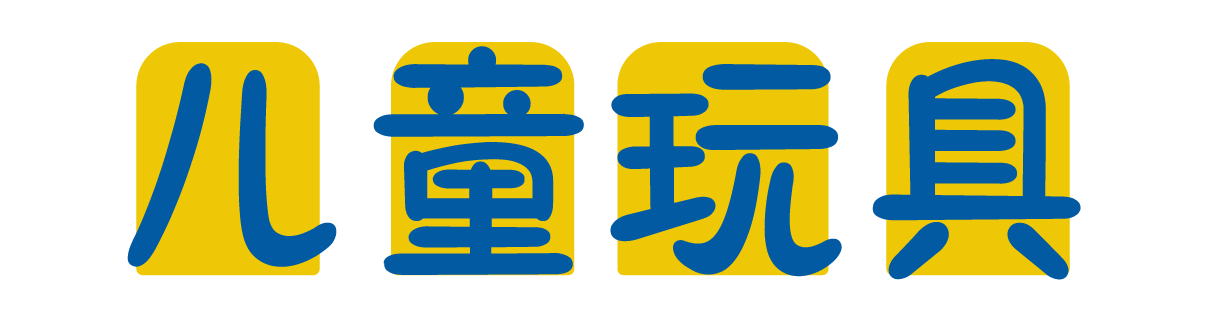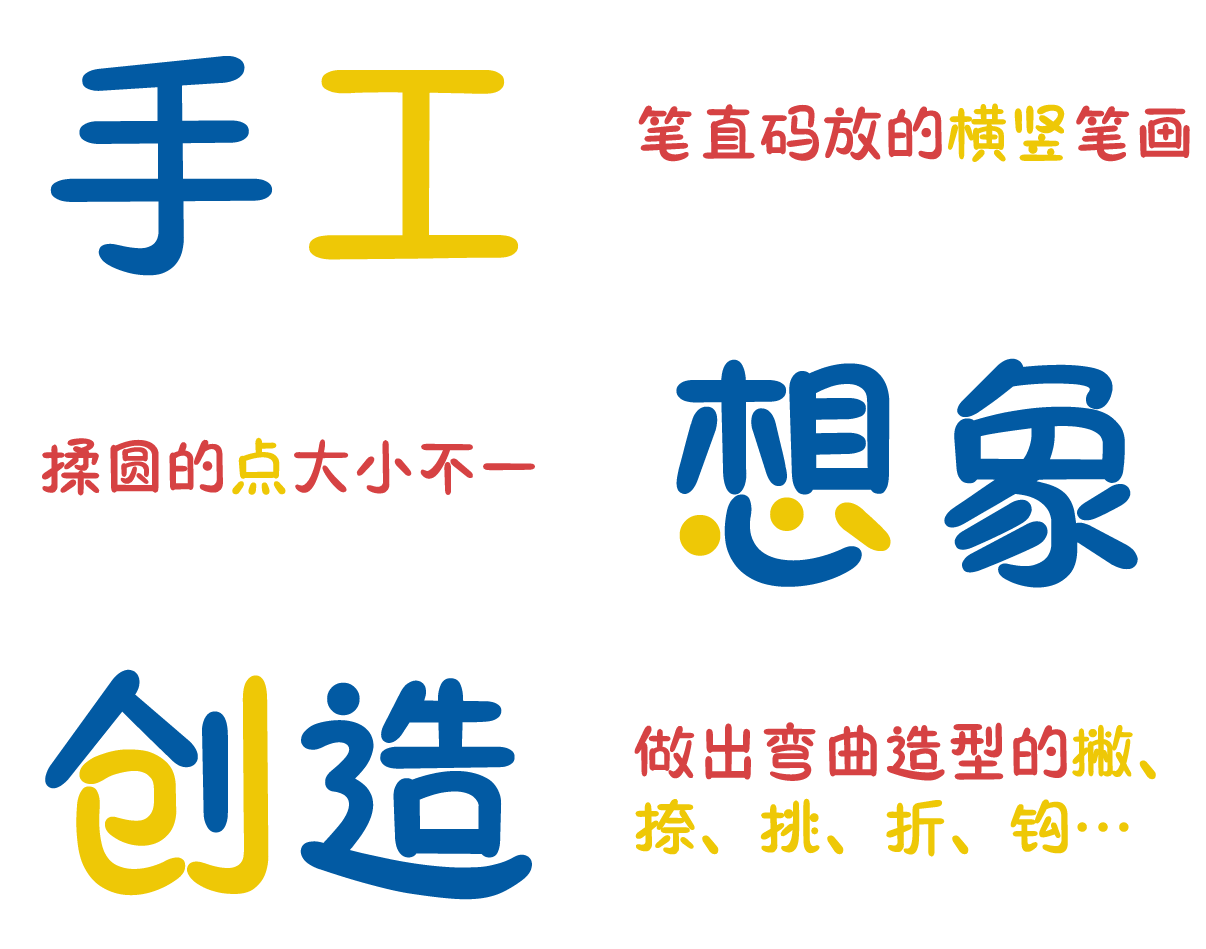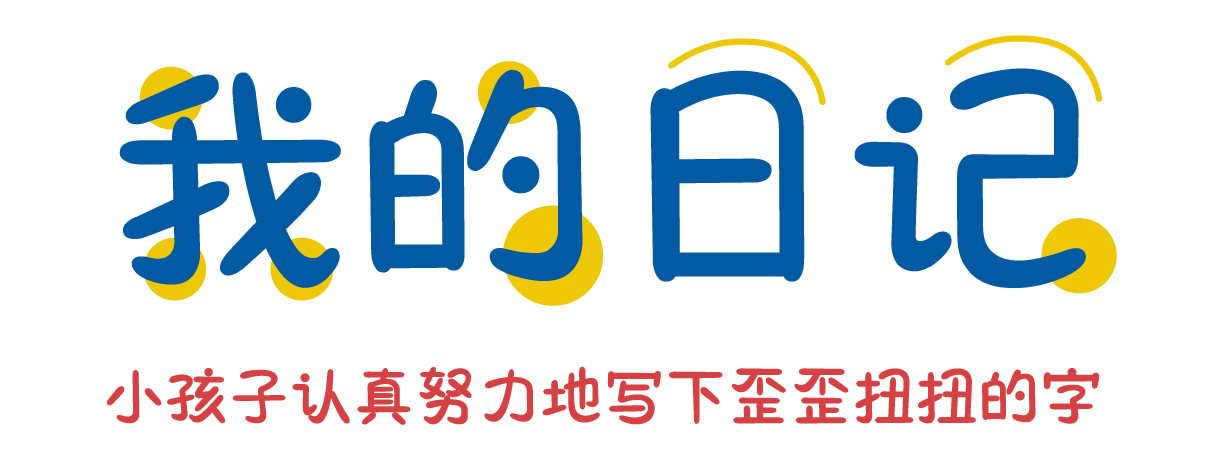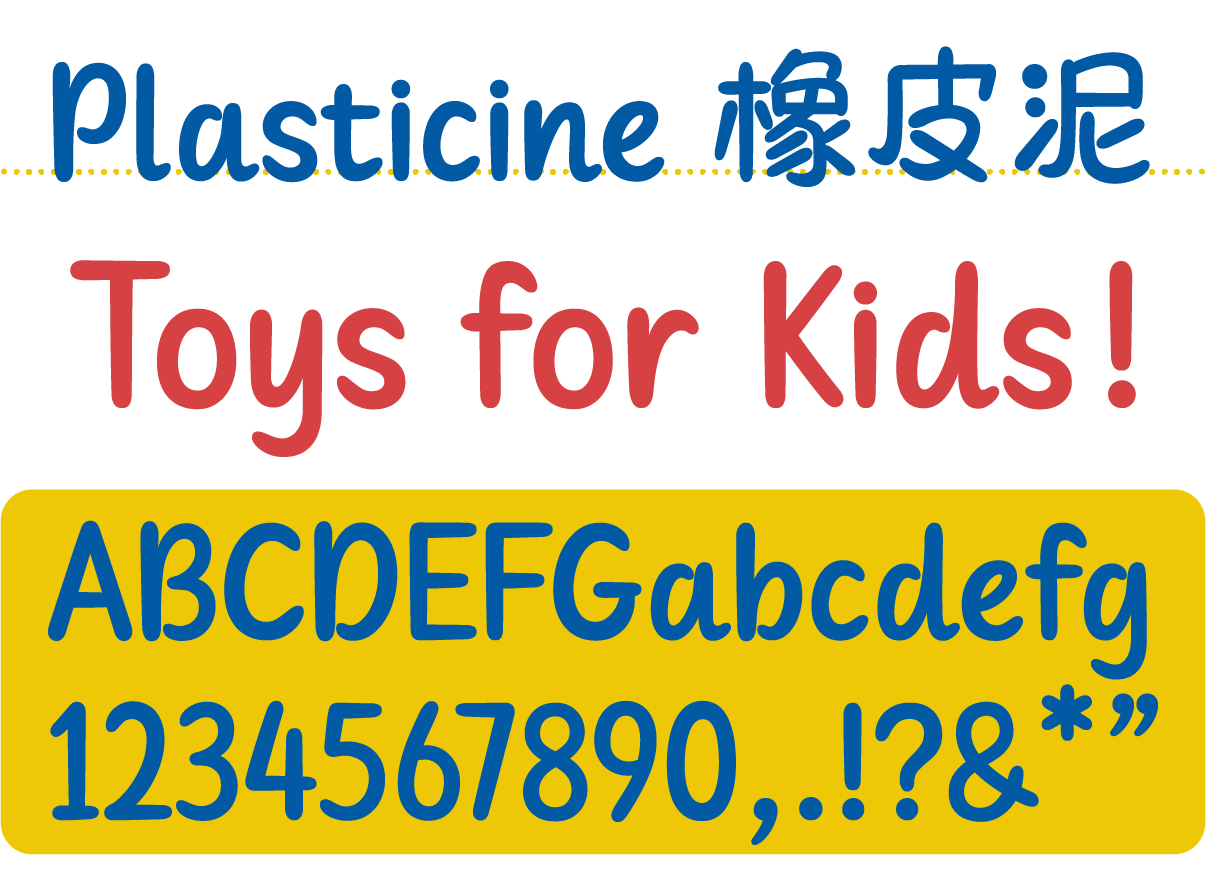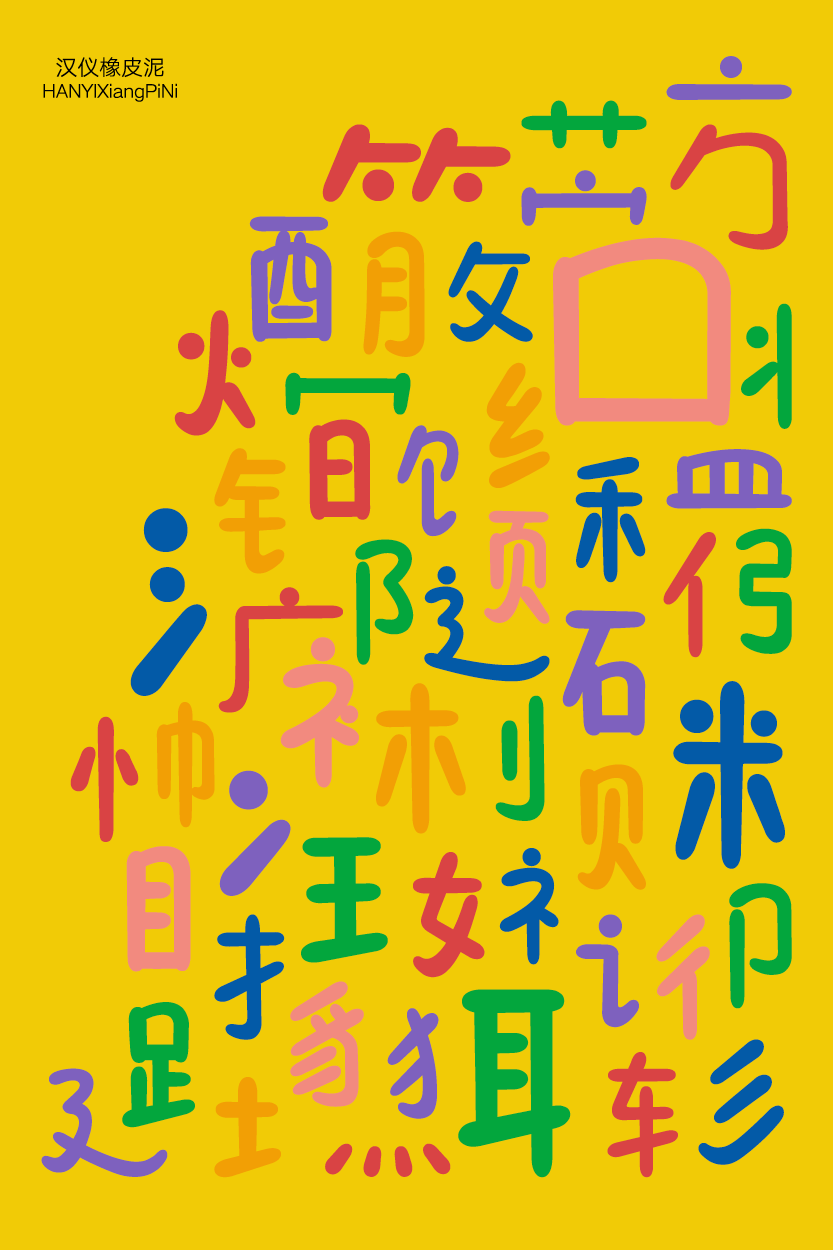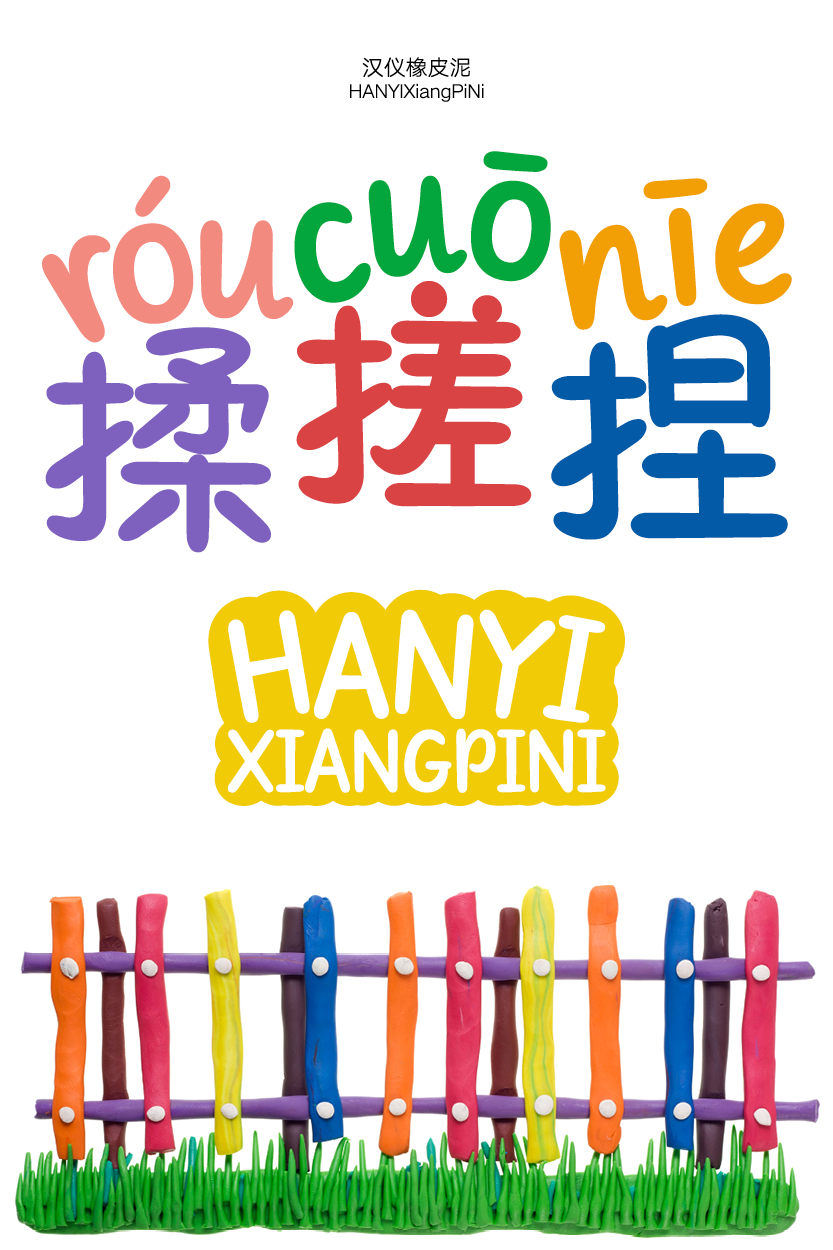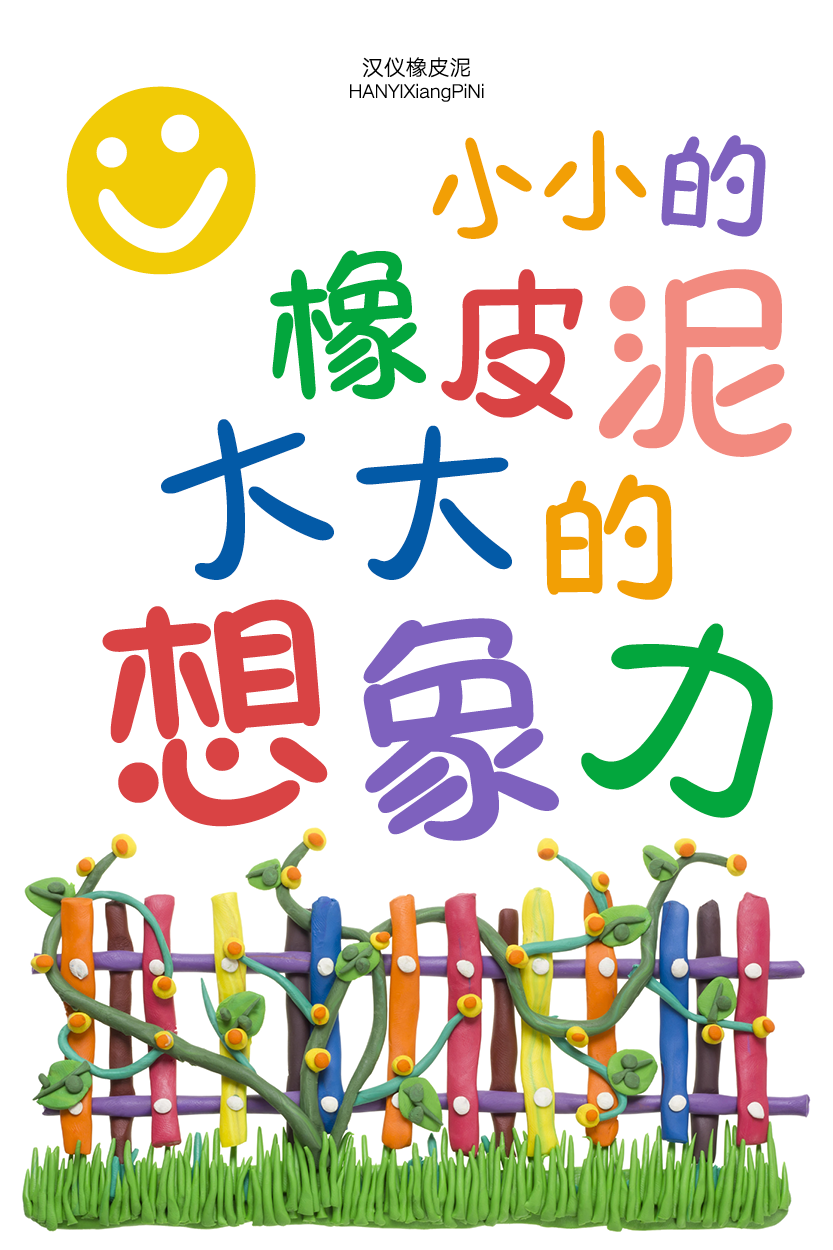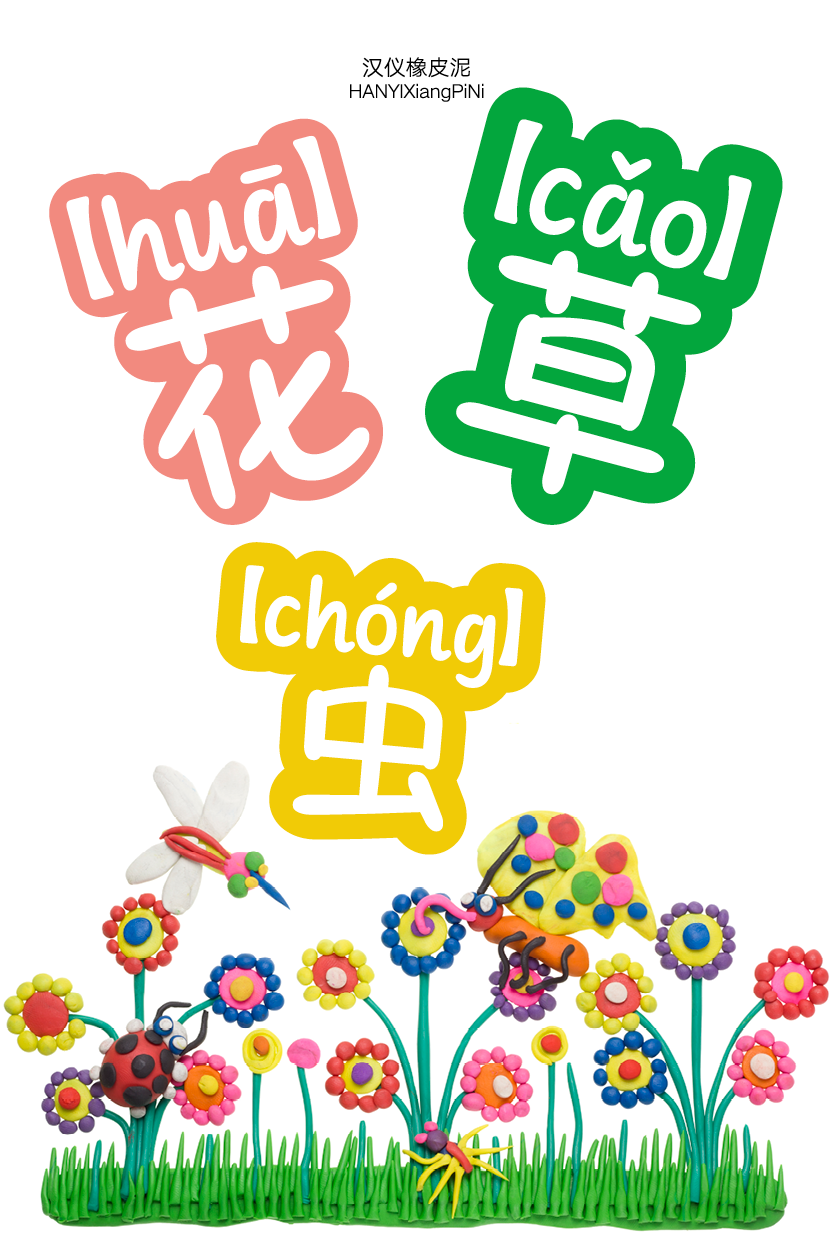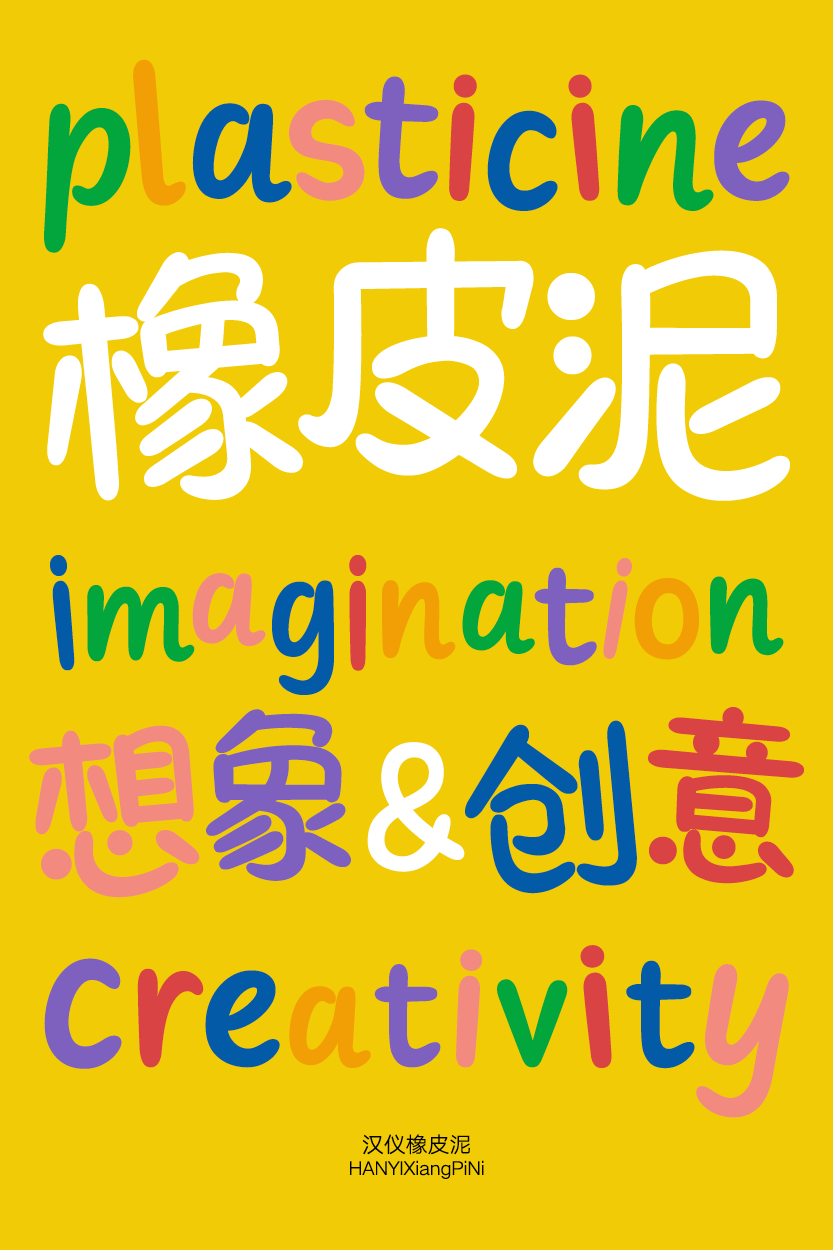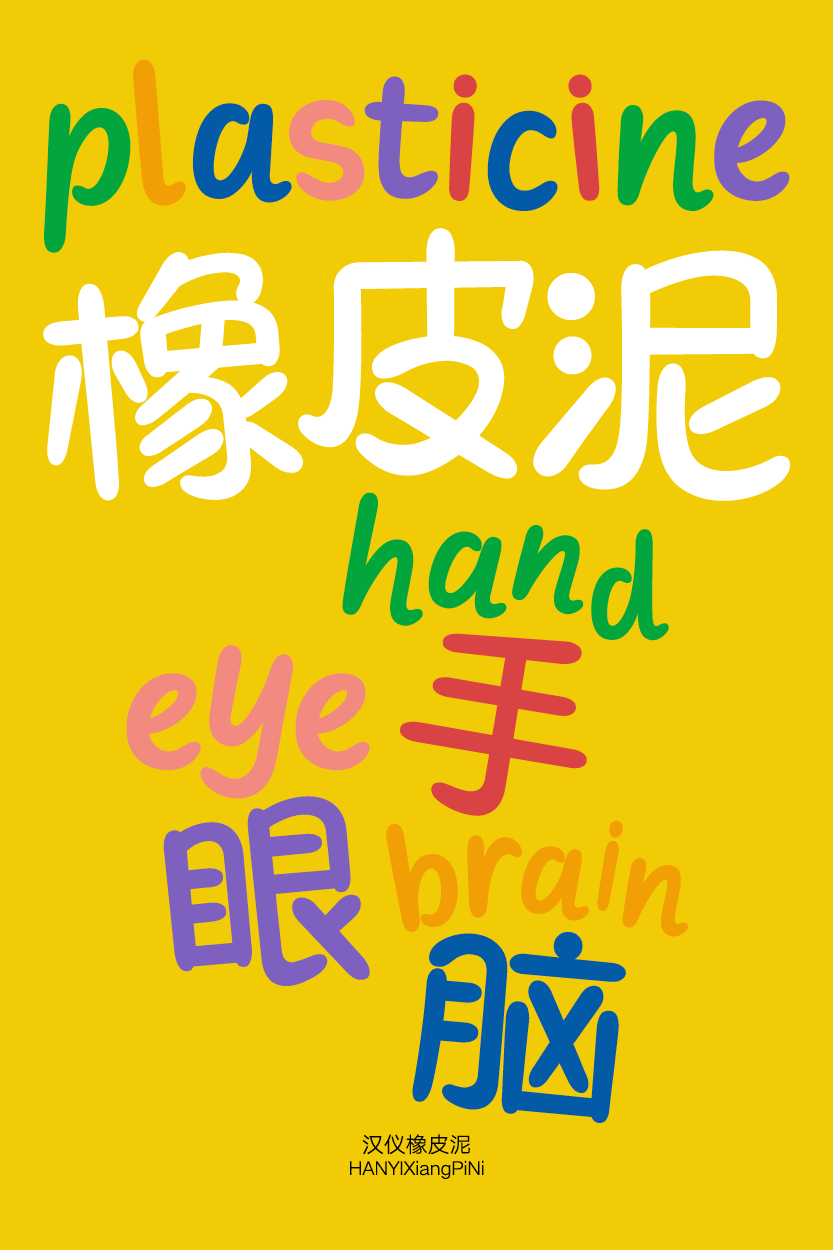
可以尽情发挥想象力的童趣字体
搓一搓、揉一揉、捏一捏,汉仪橡皮泥,出现了!这款童趣可爱的字体就像是回到了童年玩转橡皮泥的手工时间,搓出细长的横竖、揉圆大大小小的点、捏出弯曲的撇捺挑钩……最后认认真真地摆出字体的样子,完成!这款字体适合用于漫画绘本、动画节目、玩具包装等多种多样的使用场景,快乐多多,童心满满。
长方形的字形整齐而饱满。
橡皮泥搓揉出圆头圆尾的笔画,形态各异,充满童趣的巧思。
笔画的粗细略有变化,整齐之中又充满手工感。
汉仪橡皮泥的西文部分由汉仪字库西文字体设计师李田宇创作,像是橡皮泥搓揉出来的圆头长条笔画摆弄而成,有着规整又稚拙的模样。